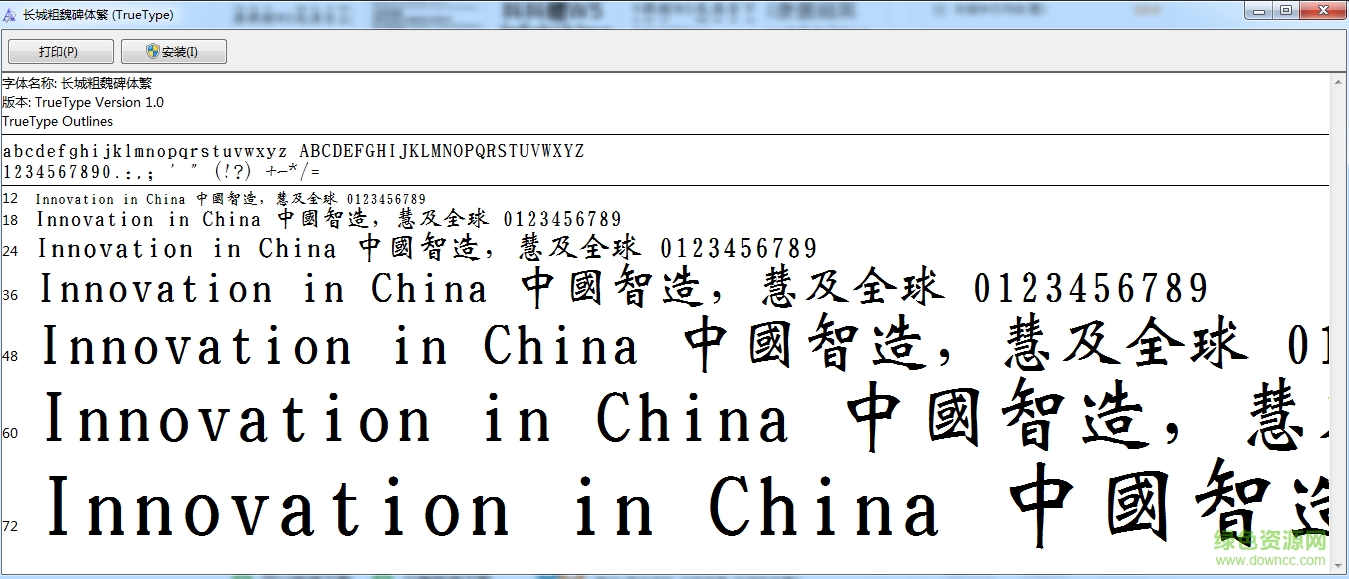
長城粗魏碑體繁是一款生動嚴謹一體、兼隸楷味道的繁體魏碑字體,適合于書法印刷、廣告創(chuàng)作等行業(yè),簡單大方的造型給人獨特的魅力和好感,綠色資源網(wǎng)誠意推薦!
魏碑風(fēng)格多樣,樸拙險峻,舒暢流麗。極有名的如《鄭文公碑》、《張猛龍碑》、《高貞碑》、《元懷墓志》及《張玄墓志》,已開隋、唐楷書法則的先河。清代中期倡導(dǎo)“尊碑抑帖”,沖破“館閣體”的束縛,碑學(xué)興起,書風(fēng)為之一變。魏碑上承漢隸傳統(tǒng),下啟唐楷新風(fēng),為現(xiàn)代漢字的結(jié)體、筆法奠定了堅實的基礎(chǔ)。但有許多摩崖石刻,并不是先行書丹上石,而是直接在石面上雕鑿的,臨寫時要注意不使刀痕夸張,免生習(xí)氣。